Сьогодні існує величезна кількість шрифтів для татуювань. Про них необхідно поговорити більш детально. Цим ми і займемося зараз.
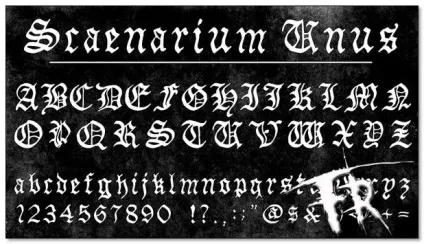
Розглянемо, які є шрифти для тату. Якщо ви підібрали собі шрифт, то це перший крок до того, що ви отримаєте необхідну татуювання. Це вже вас запорука успіху. Так що просто підберіть собі той варіант, який підійде найбільше саме вам. Татуювання повинна бути естетично красивою і акуратною.
Де підібрати шрифт для татуювання?
Підібрати шрифт для татуювання можна знайти практично скрізь. По-перше, ви зможете звернутися за допомогою в інтернет. Там є дуже багато тату шрифти онлайн. Їх ви підбираєте і розглядаєте. Якщо ви підібрали необхідний шрифт, то просто далі складаєте його ескіз.
Якщо все буде нормально, то можна бити. Саме тому необхідні ескізи. Знайти і підібрати шрифт можна в салоні. Якщо ви вибрали відповідну опцію, то його і набиваєте. Підібрати вам із задоволенням допоможуть професіонали. Там можна з легкістю здійснити підбір шрифту для тату. Вам допоможуть в цьому і порадять. Салон надає всі види шрифтів, з якими він працює і покаже вам фотографію.
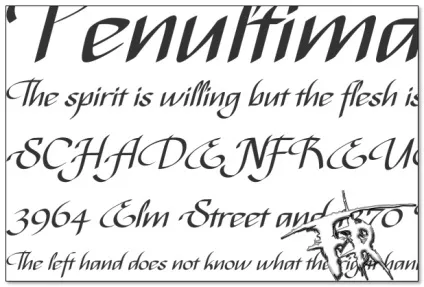
Якщо це ваша перша татуювання, то необхідно все-таки звертатися в салон, а не підбирати самостійно. Вони краще побачать, як повинна буде виглядати татуювання у вас. Та є навіть шрифти для тату онлайн підбір. Так що все нові послуги будуть вам надані, і ви отримаєте все найкраще і необхідне.
Які є шрифти для татуювань?
Підібрати шрифт для тату необхідно відразу після того, як ви вибрали собі напис. Підбирати шрифт необхідно тільки тоді, коли вже вибрана підпис. Вони повинні гармонійно виглядати поряд і доповнювати один одного. Заздалегідь необхідно розглянути і те, якого розміру буде ваша напис.
Це дуже важливо і те, що ми визначаємося з місцем, де ви будемо набивати татуювання. Отже, це може бути, наприклад, рука, шия. Часто набивають на таких частинах тіла як лопатки, поперек, кісточка і інші частини тіла. Для них є дуже багато варіантів шрифту. Там можна підібрати гарні шрифти для тату. Отже, можна підібрати чорні шрифти, а можна кольорові.
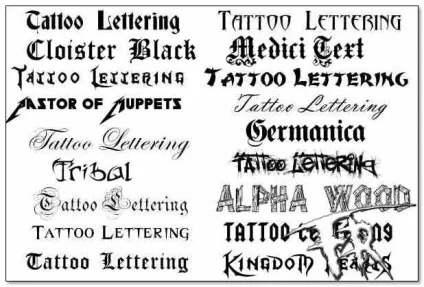
Є і підписи практично безбарвні. Ви зможете підібрати і інші варіанти, наприклад, добре підійде вам візерункові літери. Є суворі шрифти, є з візерунком. Є шрифти спеціально для дат та ініціалів. Просто необхідно підібрати собі ідеальний варіант тоді у вас зовсім не буде проблем. Якщо ви підберете те, що необхідно, то виглядати буде відмінно. Головне шрифт і фон. Вони повинні відповідати один одному. Просто підберіть собі шрифт для тату написів.
Підписи для і їх шрифт, і їх переклад
Сьогодні дуже популярні підписи на різних мовах. Є дуже багато тату шрифт для тату онлайн підібрати. Про них ми і поговоримо сьогодні. По-перше, це може бути підпис з фразою знаменної для вас. Ви можете набити ініціали коханої людини, його ім'я або прізвище. Можна набити і дату, яка має значення для вас. Дуже часто набивають щось із класики.
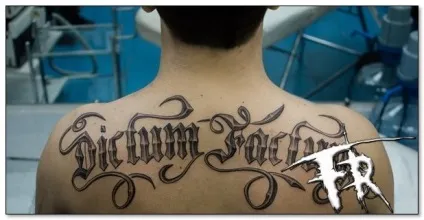
Наприклад, якісь крилаті вирази, такі як: через терни до зірок або поки живу, сподіваюся. Є дуже багато тату написи з перекладом фото, вони допоможуть вам побачити те, що ви собі наб'єте, то, що ви отримаєте в результаті.
Дуже важливо правильно переводити те, що хочете собі набити. Інакше у вас нічого не вийде. Якщо ви не будете знати переклад, то може вийти не приємна ситуація і ви отримаєте не правильну фразу. Зовсім не ту, яку б хотіли. Найчастіше роблять тату написи на руці з перекладом. Рука - це найпомітніше місце і там завжди видно те, що ви хочете написати.
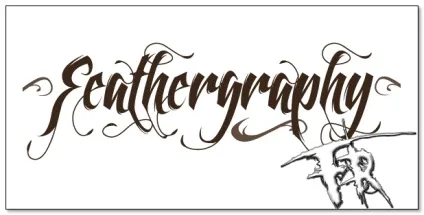
Саме тому необхідно знати переклад. Він повинен повністю відповідати тому, що ви хочете. Дуже важливо підібрати правильну напис. Її колір повинен відповідати, її фон і правильність написання. Все повинно бути красиво і акуратно.
Інакше у вас не вийде необхідний ефект і результат. Сьогодні дуже часто набивають собі схожі татуювання, як, наприклад, у якихось акторів. Часто шукають татуювання на руці. Про них ми і поговоримо в нашій статті. Дуже часто буває так, що ви дивитеся на когось і задумав, його татуювання набагато краще і крутіше виглядає. Часто таке буває зі знаменитостями.
Татуювання як у популярних зірок
Розглянемо більш детально зірок, які мають багато татуювань. Тут, безсумнівно, перемагає саме глутамат. Його татуювання знаходяться по всьому тілу. Знайти їх зовсім не складно.
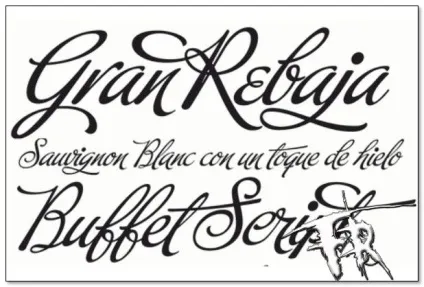
Можна навіть Тіматі і його татуювання його кліпи і подивитися на татуювання, які у нього є. Дуже важливо те, що там можна знайти абсолютно всі варіанти, наприклад, кольорові татуювання, чорні, з тінню, що не затемнені. Важливо, що татуювання Тіматі завжди оновлюються.
Він постійно щось нове собі набиває. Раніше кожна тату Тіматі мала нове татуювання. Скоро у нього не залишиться жодного вільного місця на тілі. Все буде в татуюваннях. Можна знайти і тату кліп. Він включає в себе всі його татуювання. Майстри просто обожнюють цього співака. На ньому можна знайти будь-які татуювання.